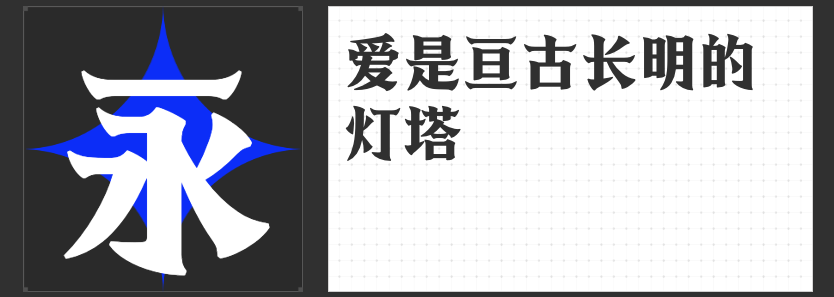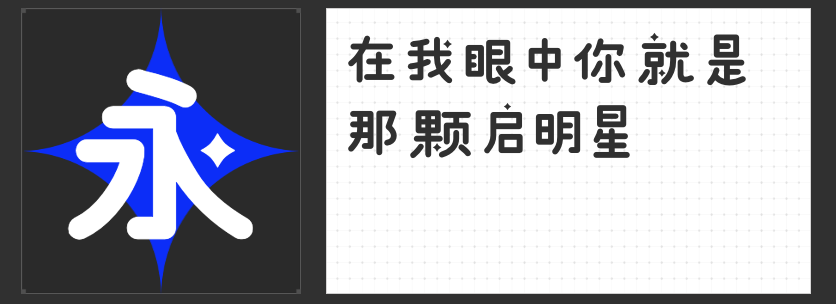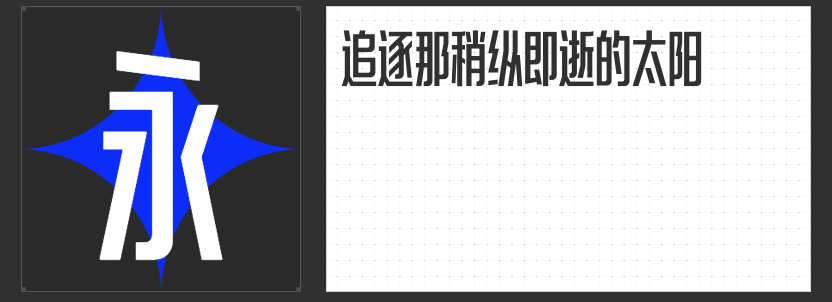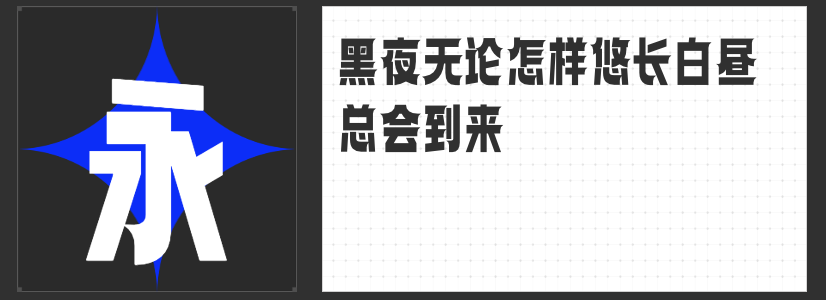
“高手兵克”系列字体:设计中的创意之选
在设计的世界里,字体不仅是文字的呈现,更是情感和风格的传递者。今天,我要向大家推荐一组极具特色且实用性强的字体系列——“高手兵克”。这个系列中的每一款字体都经过精心设计,旨在为设计师们提供更多元化的创意选择。接下来,让我们一起看看其中的四款明星字体。
1.高手兵克侠客体
这款字体以其独特的笔画设计脱颖而出,笔画中加入的上挑特点仿佛赋予了文字生命,让人联想到侠客般的放荡不羁。其古风韵味十足,非常适合用于标题或logo设计中,能够迅速抓住观众的眼球,营造出一种独特的文化氛围。
2.高手兵克星耀体
这款字体以其圆润的字形和可爱的小星星装饰点笔画,给人一种轻松愉悦的感受。无论是用于儿童产品的包装,还是活泼可爱的品牌宣传,都能完美契合,增添一份童真与梦幻。
3.高手兵克雷霆体
这款字体很可能以刚劲有力的笔画和动感十足的设计著称,适合表现力量、速度与激情的主题,为设计作品注入强烈的视觉冲击。
4.高手兵克高级黑
在简约风盛行的当下,这款字体以其简洁大方的设计和出色的可读性脱颖而出。无论是用于正式的商务文件,还是高端的品牌宣传,都能展现出一种稳重与大气,彰显品味与格调。
综上所述,“高手兵克”系列字体以其多样化的风格和卓越的实用性,成为了设计师们不可或缺的创意工具。无论是想要营造古风韵味,还是追求可爱梦幻,亦或是展现力量与速度、简约大气,都能在这个系列中找到满意的选择。快来尝试“高手兵克”系列字体,为你的设计作品增添一抹独特的魅力吧!